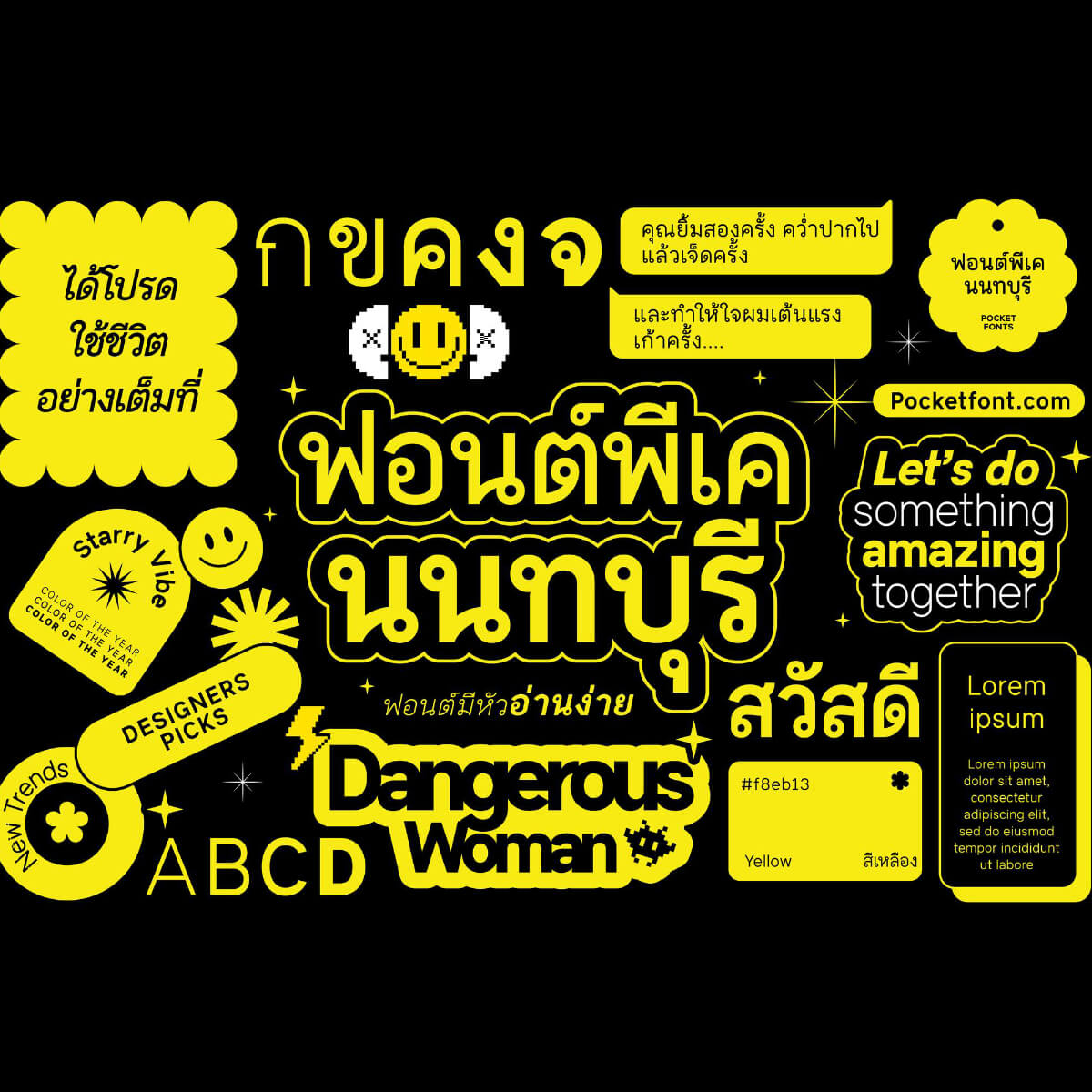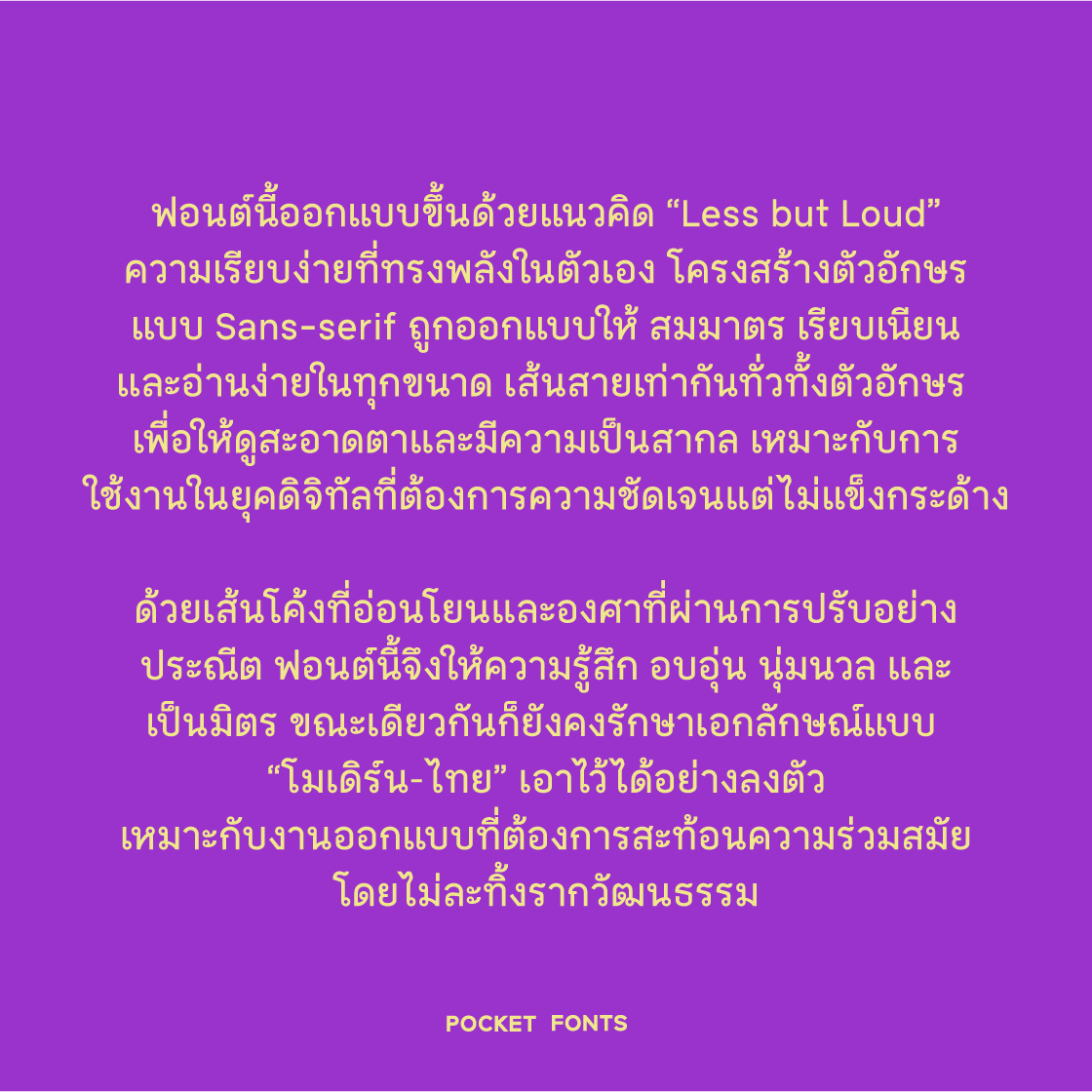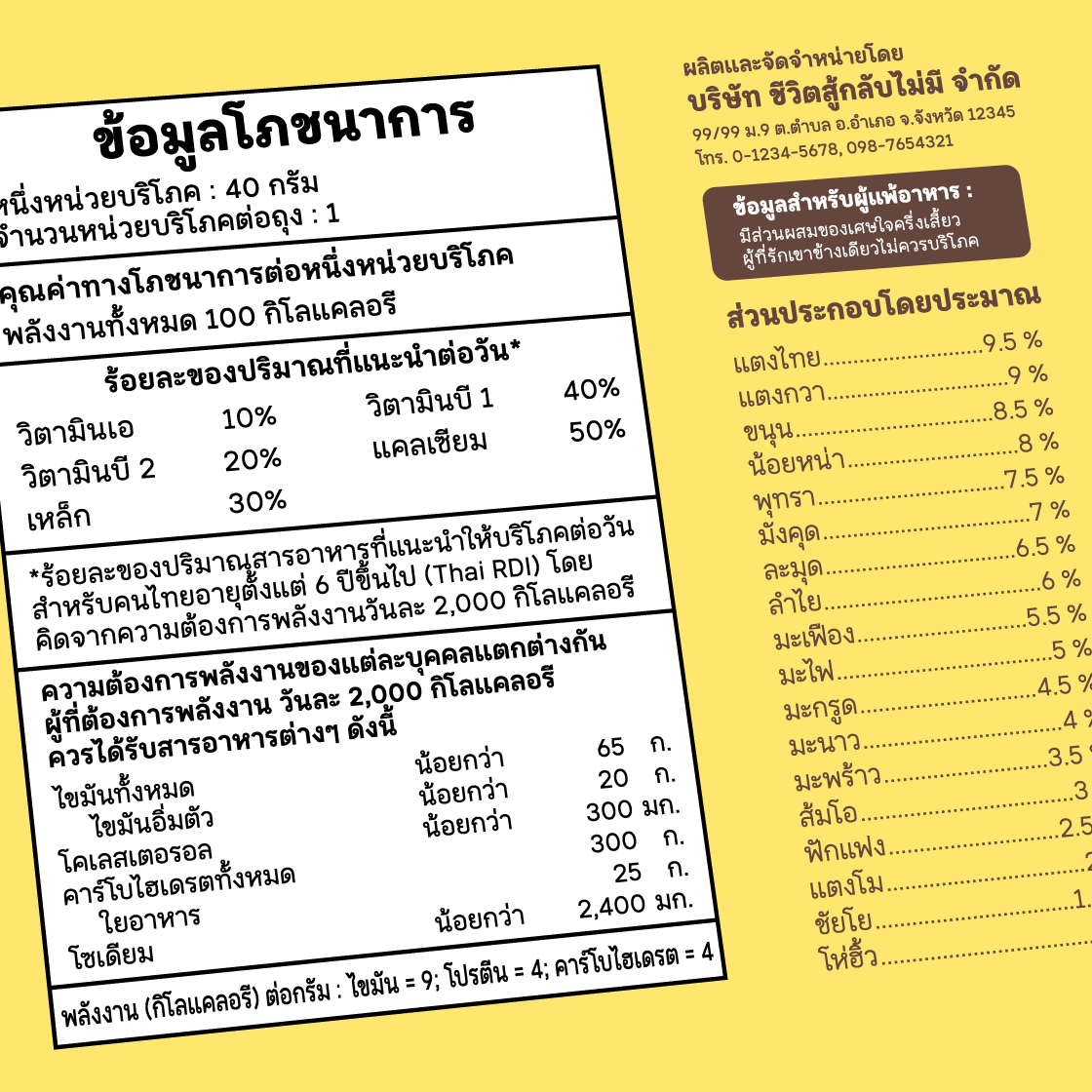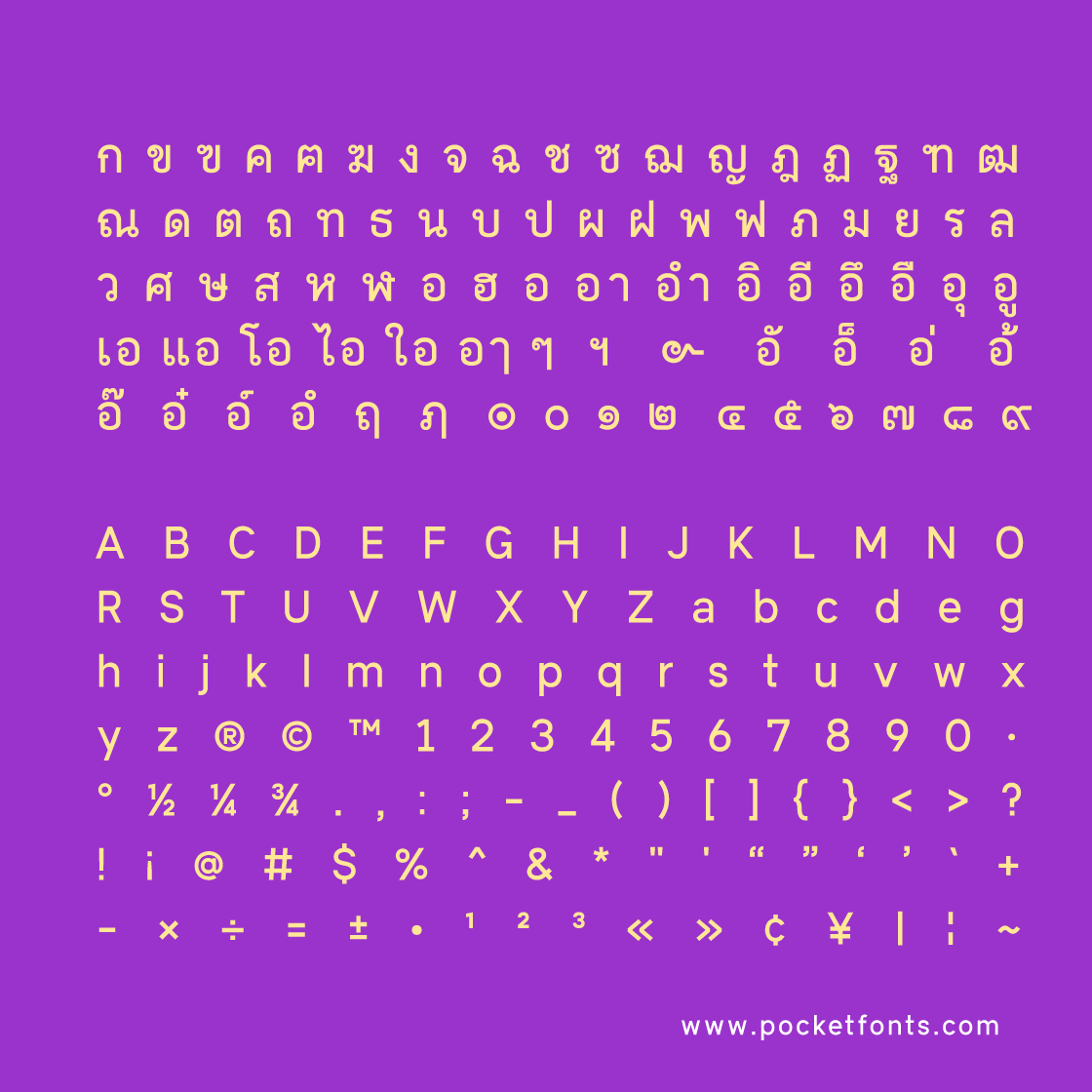
พีเค นนทบุรี (PK Nonthaburi)
พีเค นนทบุรี ออกแบบมาเพื่อสะท้อนความเป็นทางการอย่างมีระดับ พร้อมกลิ่นอายความโมเดิร์นที่เข้ากับยุคสมัย ด้วยเส้นสายที่มั่นคงและหัวฟอนต์ที่ชัดเจน PK Nonthaburi จึงเหมาะกับงานหลากหลาย ตั้งแต่งานที่ต้องการความเป็นทางการ ไปจนถึงงานดีไซน์ที่ต้องการความน่าเชื่อถือและความทันสมัยในคราวเดียว
มีทั้งหมด 5 น้ำหนัก + Variable ปรับน้ำหนักได้อย่างละเอียด